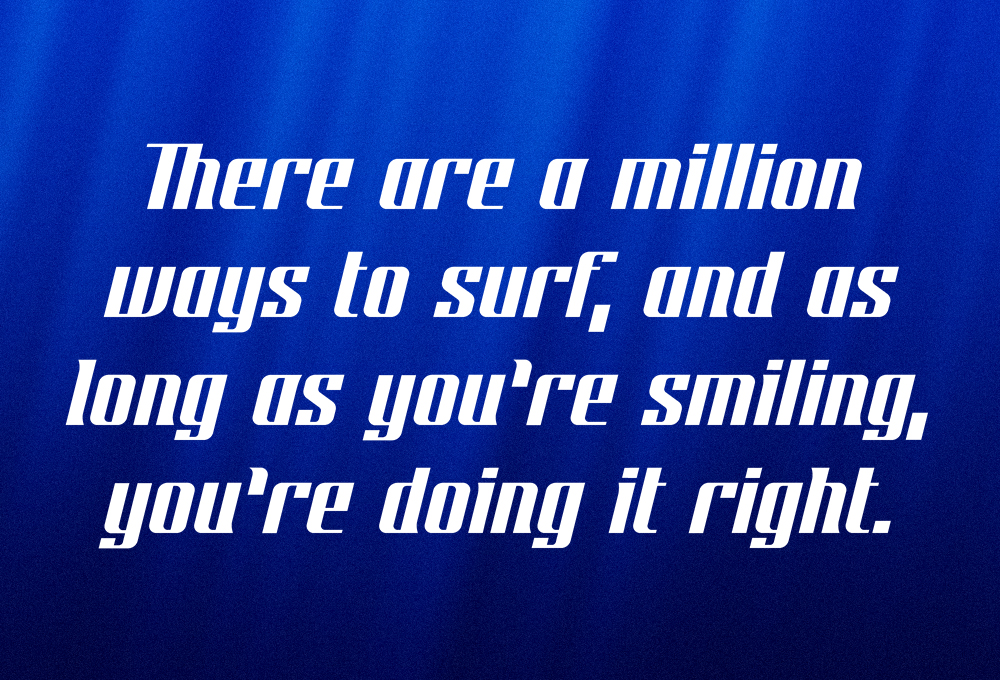
Бесплатный шрифт "Strandhill"
В начале года начал заниматься серфингом и решил попробовать сделать дисплей шрифт вдохновленный этим спортом. Спустя 9 месяцев и много прокрастинации вот результат.Если кому-то как нибудь он пригодится буду рад увидеть что из этого получилось))